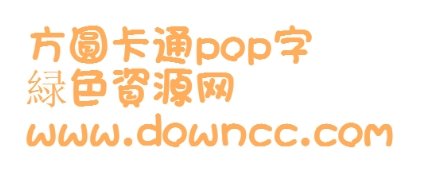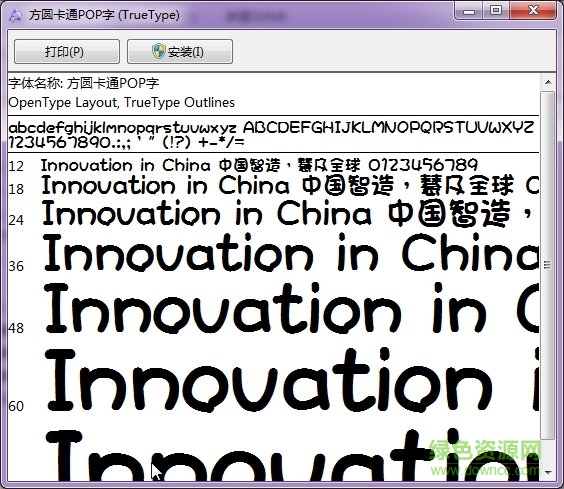
方圓卡通pop字是一款書寫流暢、字跡Q萌的pop字體,中英文都有著活潑可愛的造型,自帶粗黑效果,讓文字更加顯眼,讓閱讀體驗更佳,喜歡的朋友就來綠色資源網(wǎng)下載使用吧!
方圓卡通POP字體是一款可愛幼圓字體,字體線條粗細適中,字形呈卡通,飄逸大方得體,整體效果非常的出眾,并且字庫完整,可用于出版印刷字體、廣告設(shè)計字體、網(wǎng)頁設(shè)計字體、包裝設(shè)計字體、屏幕顯示字體等。
方圓卡通POP字體是方圓字體庫中一款獨特字體,兼具藝術(shù)字體、幼圓字體和pop字體的風格,可用于出版印刷字體、廣告設(shè)計字體、網(wǎng)頁設(shè)計字體、包裝設(shè)計字體、屏幕顯示字體等!